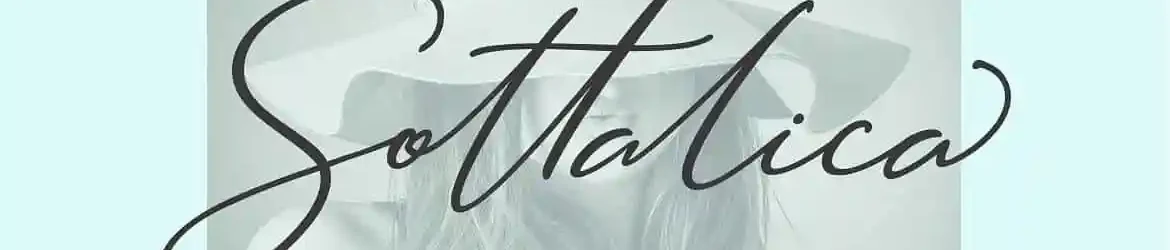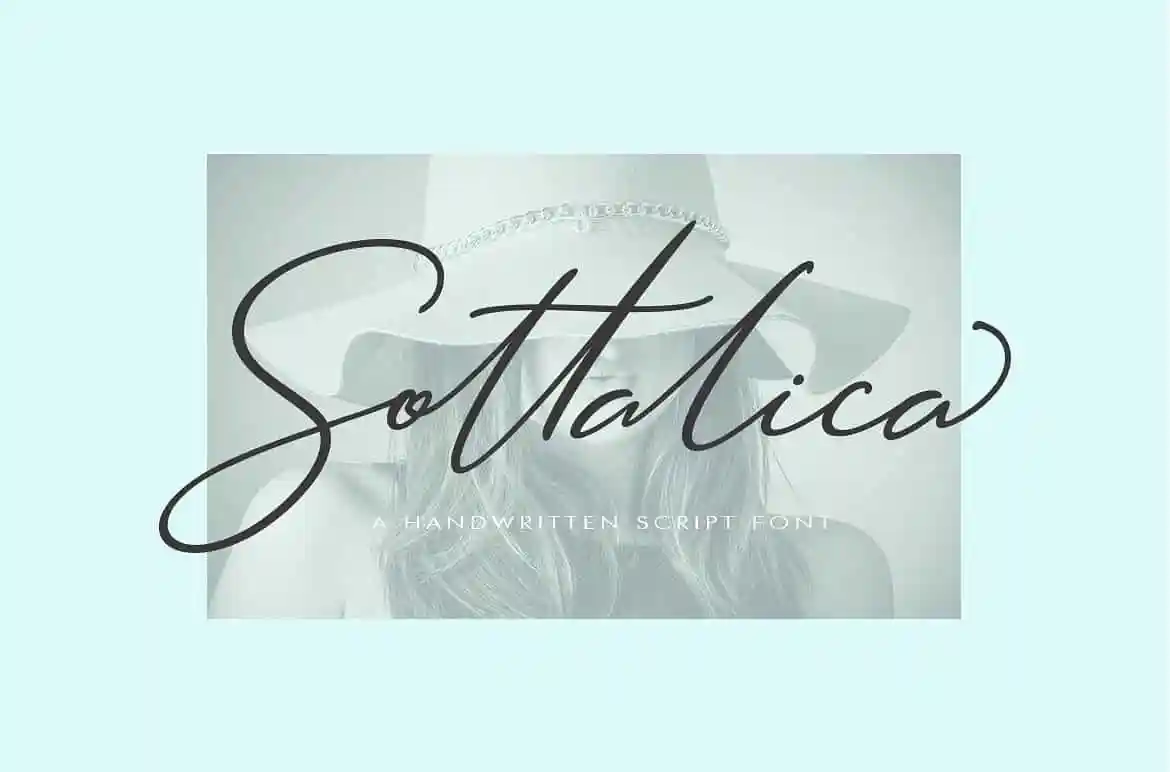
Sottalica Script Font
Aqui está uma descrição em português para a página de download da font ‘Sottalica Script Font’: Seja você um designer criando trabalhos delicados e delicados, ou até mesmo alguém que deseja adicionar um toque suave ao seu projeto editorial, Sottalica Script é perfeito. Este script moderno traz o estilo atual das escritas manuscritas para um uso variado em marcas, convites de casamento, revistas, tachinhas, cartões de negócios, frases e posters. Sottalica foi desenhada e compartilhada pela designer mightype e apresenta uma aparência incrivelmente manuscrita. É perfeito para qualquer aplicação que seja envolvente e delicada, criando um toque único em seu trabalho de design. Experimente o Sottalica Script Font se você deseja adicionar tenderness ao seu próximo projeto visual.